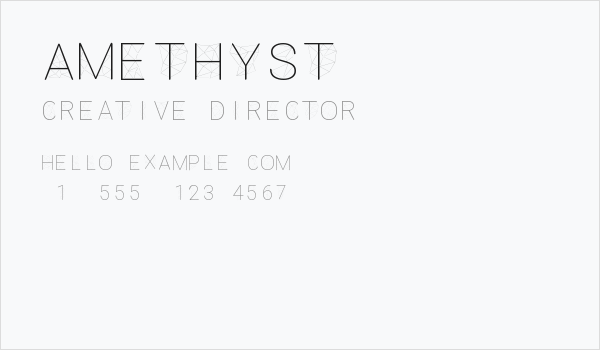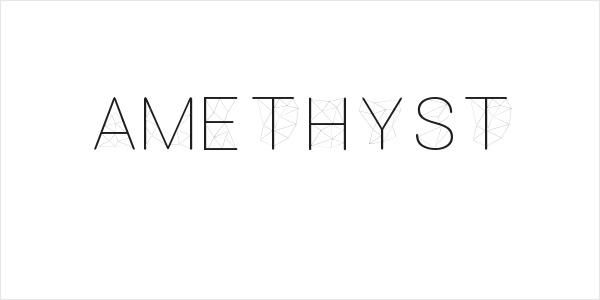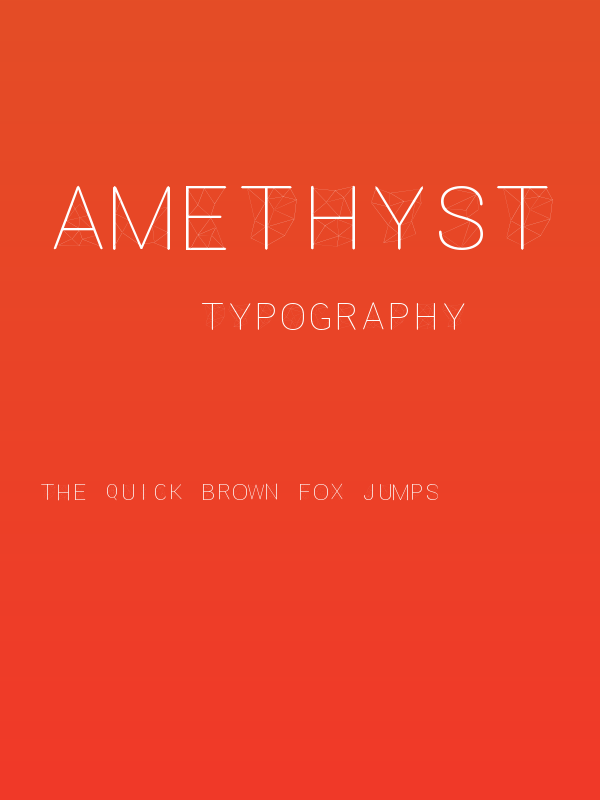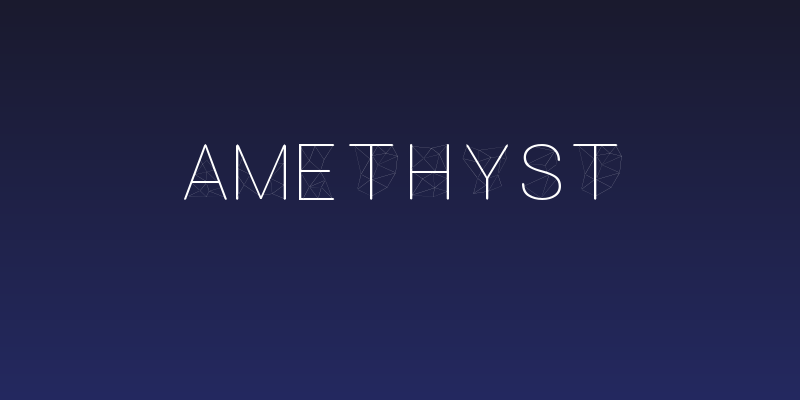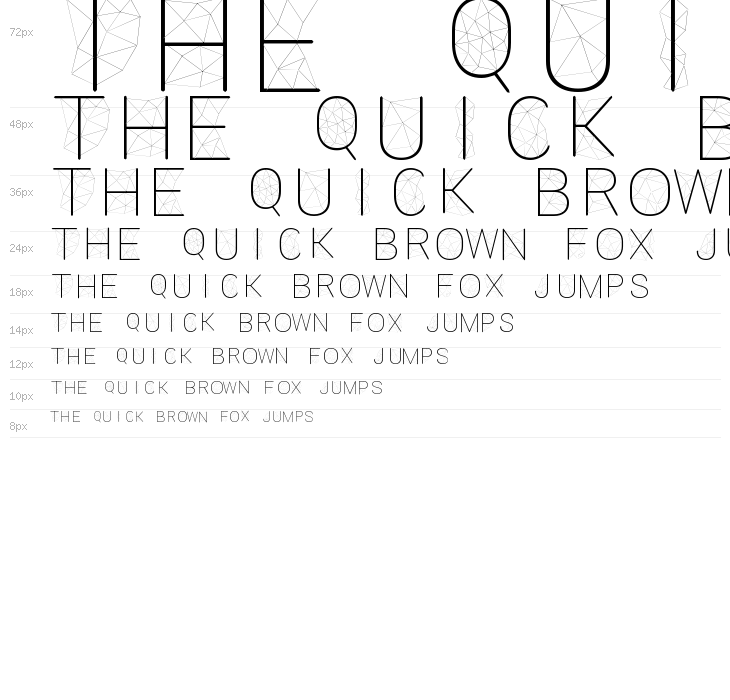
Amethyst Font
Fonts by Ivanna Jude Albea Israel
| Caz de utilizare | Logos, Posters, Artistic projects |
| Proiecte propuse | Ideal for branding, posters, and artistic projects where a modern and decorative touch is desired. |